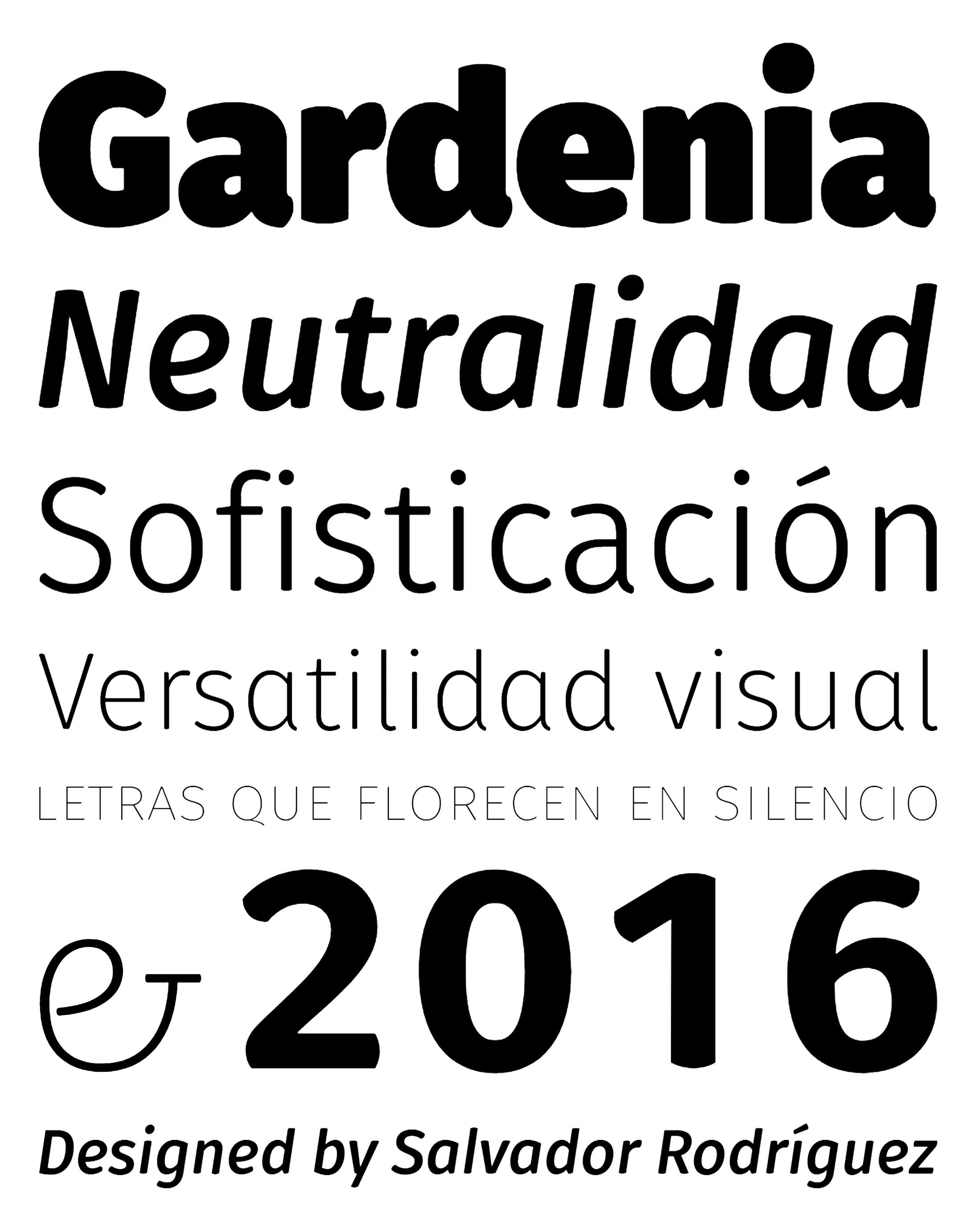
| Año | 2016 |
| Créditos | Salvador Rodríguez |
| Descripción | Gardenia es una tipografía sans-serif grotesca. Viene en 9 pesos con sus correspondientes itálicas. Fue diseñada por Salvador Rodríguez en 2015/2016. |
| Familia(s) | Gardenia Thin, Gardenia Thin Italic, Gardenia Ultralight, Gardenia Ultralight Italic, Gardenia Light, Gardenia Light Italic, Gardenia Book, Gardenia Book Italic, Gardenia Regular, Gardenia Regular Italic, Gardenia Bold, Gardenia Bold Italic, Gardenia Extrabold, Gardenia Extrabold Italic, Gardenia Black, Gardenia Black Italic, Gardenia Ultrablack, Gardenia Ultrablack Italic |
| Estilos | 18 |
| Fundidora | W Type Foundry |